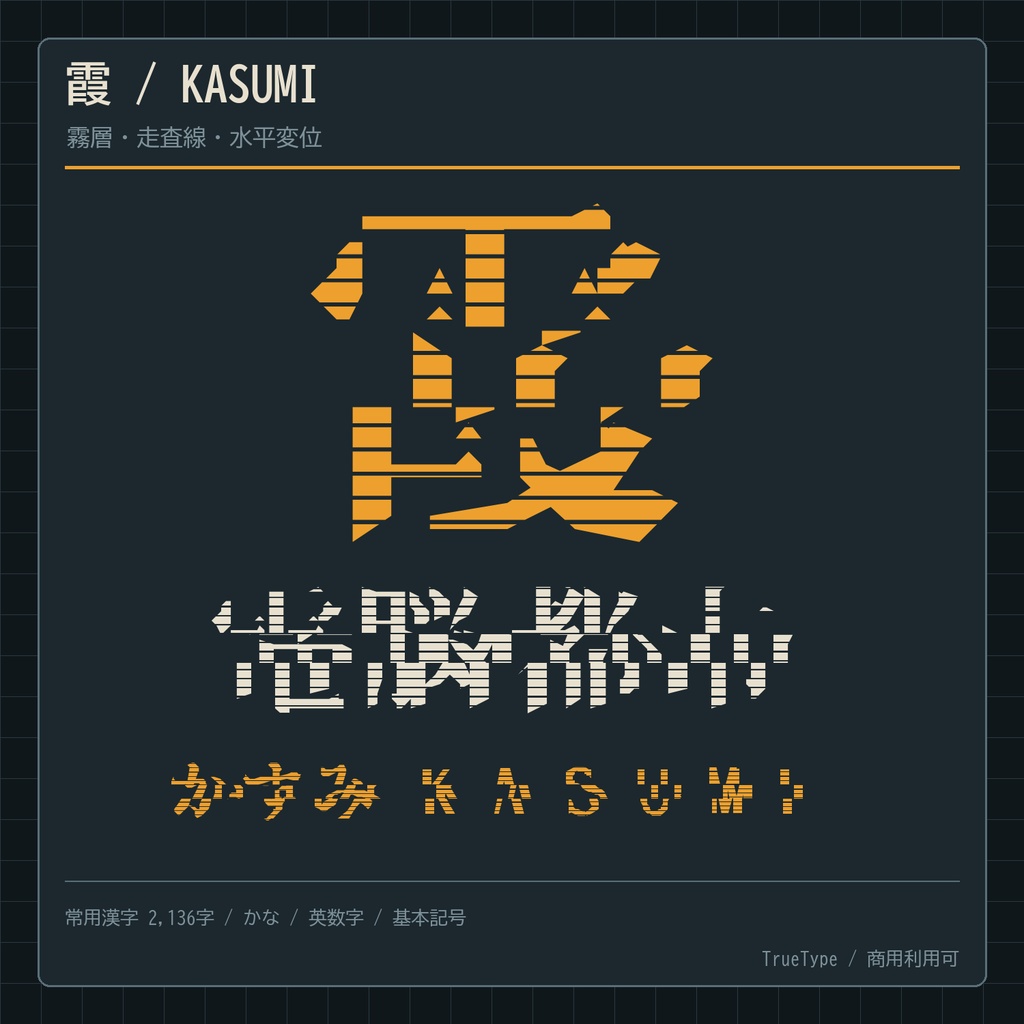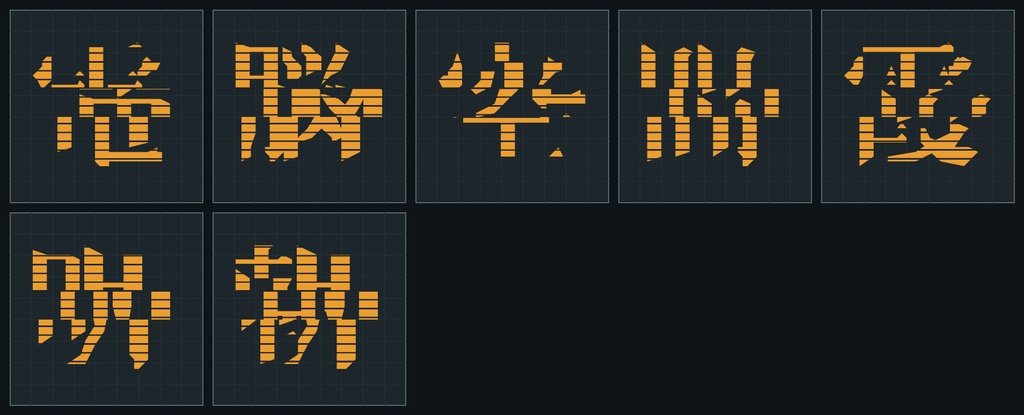
【霞 / KASUMI】霧状スキャンライン日本語フォント|常用漢字2,136字収録
【霞 / KASUMI】 文字が水平の霧層へ分解され、少しずつ位置をずらしながら再結合する サイバー・グリッチ系の日本語ディスプレイフォントです。 スキャンライン状の切れ目と三層の変位により、通信障害、電脳空間、都市の残像、 霞やノイズのような表情を作ります。 ■ 価格 980円 ■ 形式 TrueType(TTF) / Windows・macOS ■ 収録 2,542文字(空白を含む) 常用漢字:2,136字 ひらがな・カタカナ・英数字・全角英数・基本記号 追加字:「霞」 ■ 特徴 ・字画を横方向のスキャンラインへ分解 ・上部・中央・下部を異なる量だけ水平変位 ・漢字、かな、英数を同じグリッチ規則で統一 ・GlyphWiki KAGEデータから独自形状へ再構築 ■ おすすめ用途 SF・サイバー作品、ゲームUI、映像タイトル、音楽ジャケット、配信画面、ロゴ ■ 利用 個人・商用利用可。ロゴ、動画、ゲーム、印刷、配信、同人・商業作品に使用できます。 クレジット不要です。フォントデータの再配布・共有・転売は禁止です。 詳細はZIP内の利用規約をご確認ください。 ※グリッチと細い分断部を含むため、28px以上の見出し用途を推奨します。